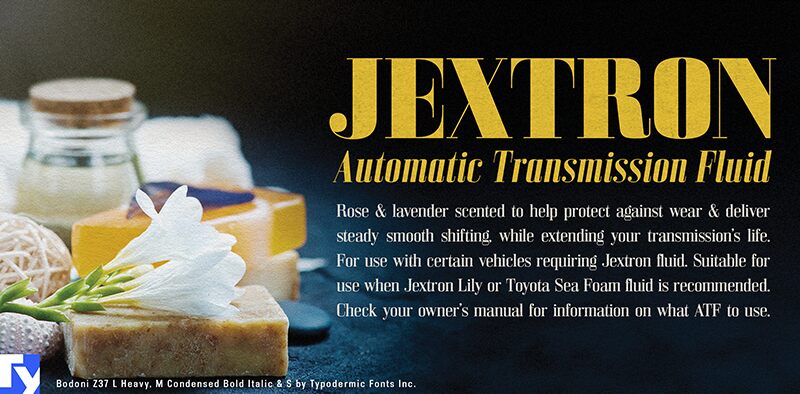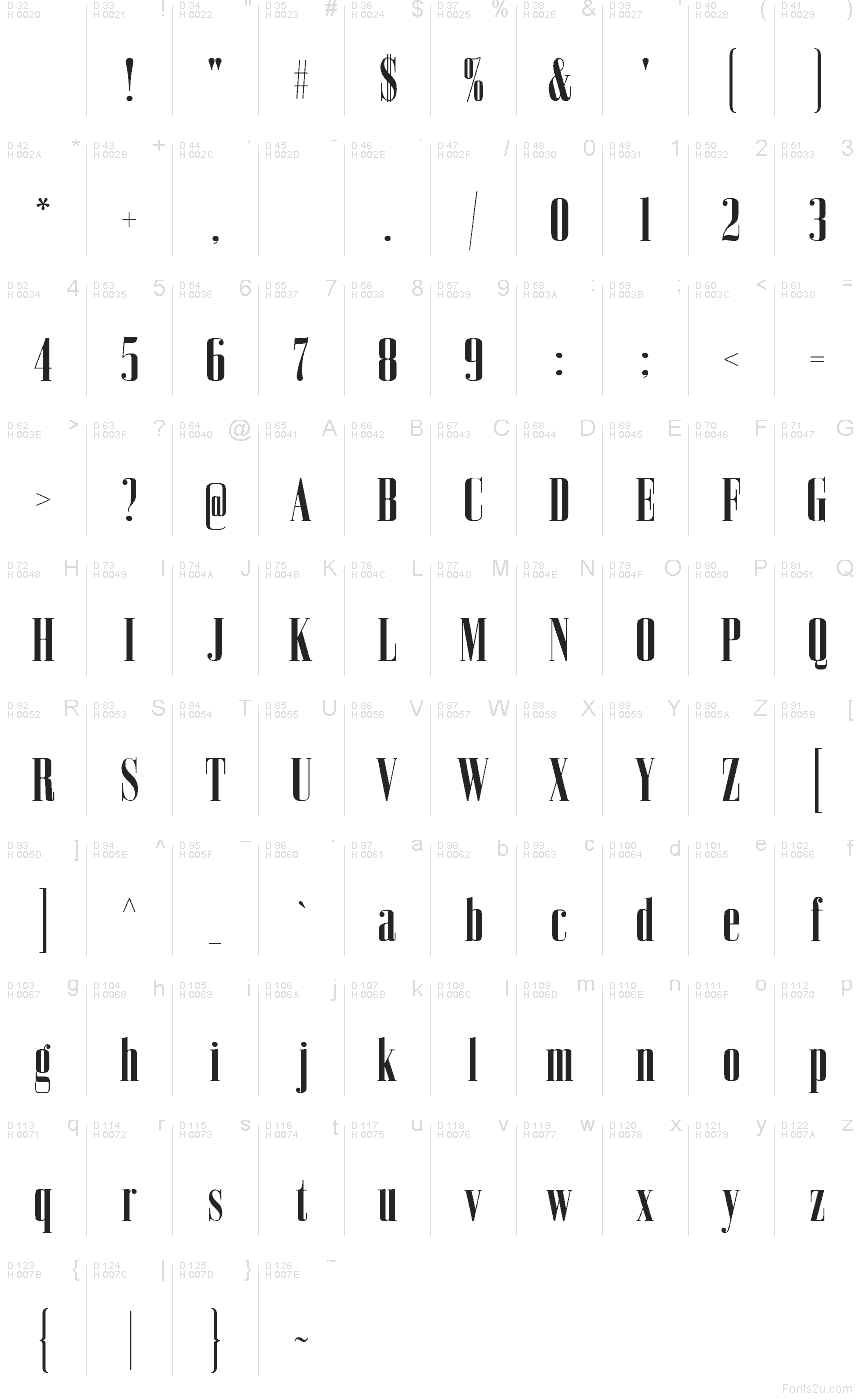
Bodoni Z37 è un'interpretazione contemporanea dell'eleganza geometrica di Giambattista Bodoni. Disegnato con un'attenzione meticolosa alle proporzioni e al ritmo, questo carattere conserva il contrasto drammatico e la struttura raffinata che definiscono lo stile classico, adattandoli però alla tipografia moderna.
Le sue curve dai lati piatti mettono sottilmente in risalto lo spirito geometrico di Bodoni, mantenendo le forme nitide sugli schermi ad alta risoluzione di oggi senza sacrificare la loro naturale calore. Il risultato è un design che bilancia drammaticità e disciplina, ideale per editoriali di moda, libri d'arte, packaging di lusso e altri progetti in cui chiarezza e raffinatezza vanno di pari passo.